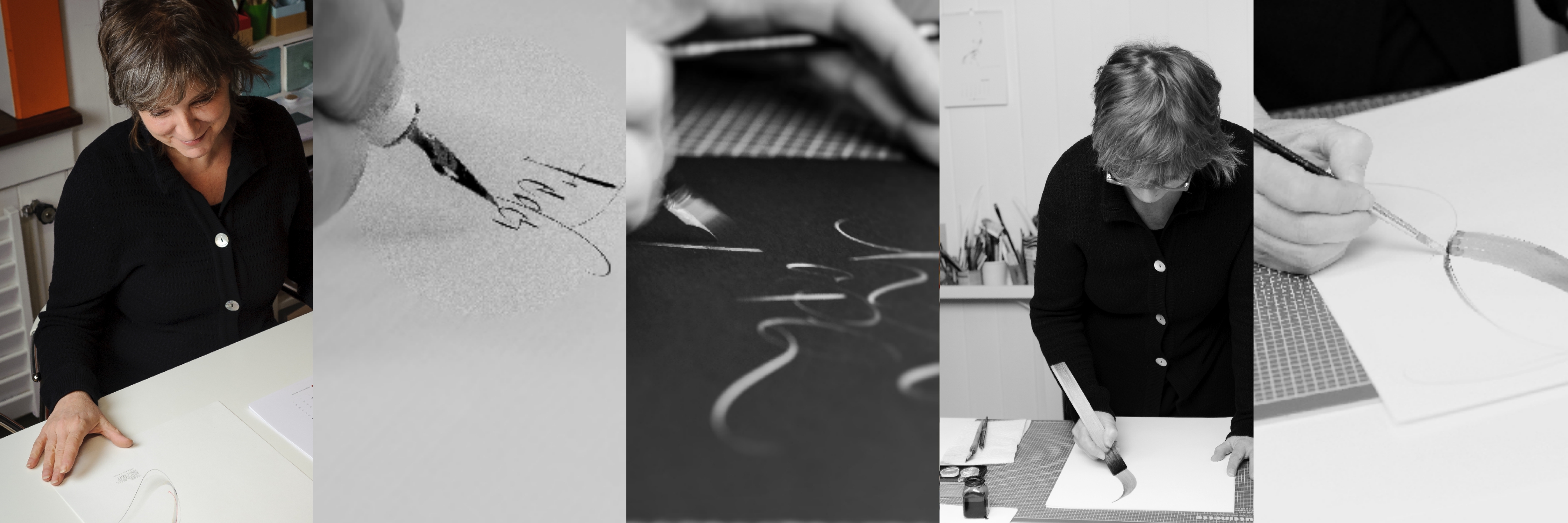
Seit jenem magischen Moment, als meine Hand ihren ersten Buchstaben formte (es war ein grosses „B“ unter der fachlichen Anleitung meines grossen Bruders) bin ich fasziniert vom Schreiben. Meine intensive Beschäftigung mit der Kalligrafie hat vor über elf Jahren begonnen. „Sie brauchen also ein gewisses Mass an Besessenheit, um ein zügiges Schreiben zu beherrschen“, las ich da in meinem ersten Kalligrafiebuch – und kann nur bestätigen, es hilft! Inzwischen vergeht kaum ein Tag ohne das Eintauchen in diese Momente auf Papier – und ich staune wie damals darüber, was entsteht.
Ich liebe es, mit traditionellen und mit meinen eigenen Formen, mit den unterschiedlichsten Werkzeugen und Materialien zu experimentieren und dabei meine Schriftzüge zu verfeinern. In unserer Zeit, in der wir mit E-Mails und anderen digitalen Kommunikationsmitteln überflutet sind, lebt meine Arbeit von der Achtsamkeit auf einen Strich, vom Geräusch meiner Feder auf rauem Papier, vom Entstehenlassen der Formen und Farben auf dem Schreibuntergrund.